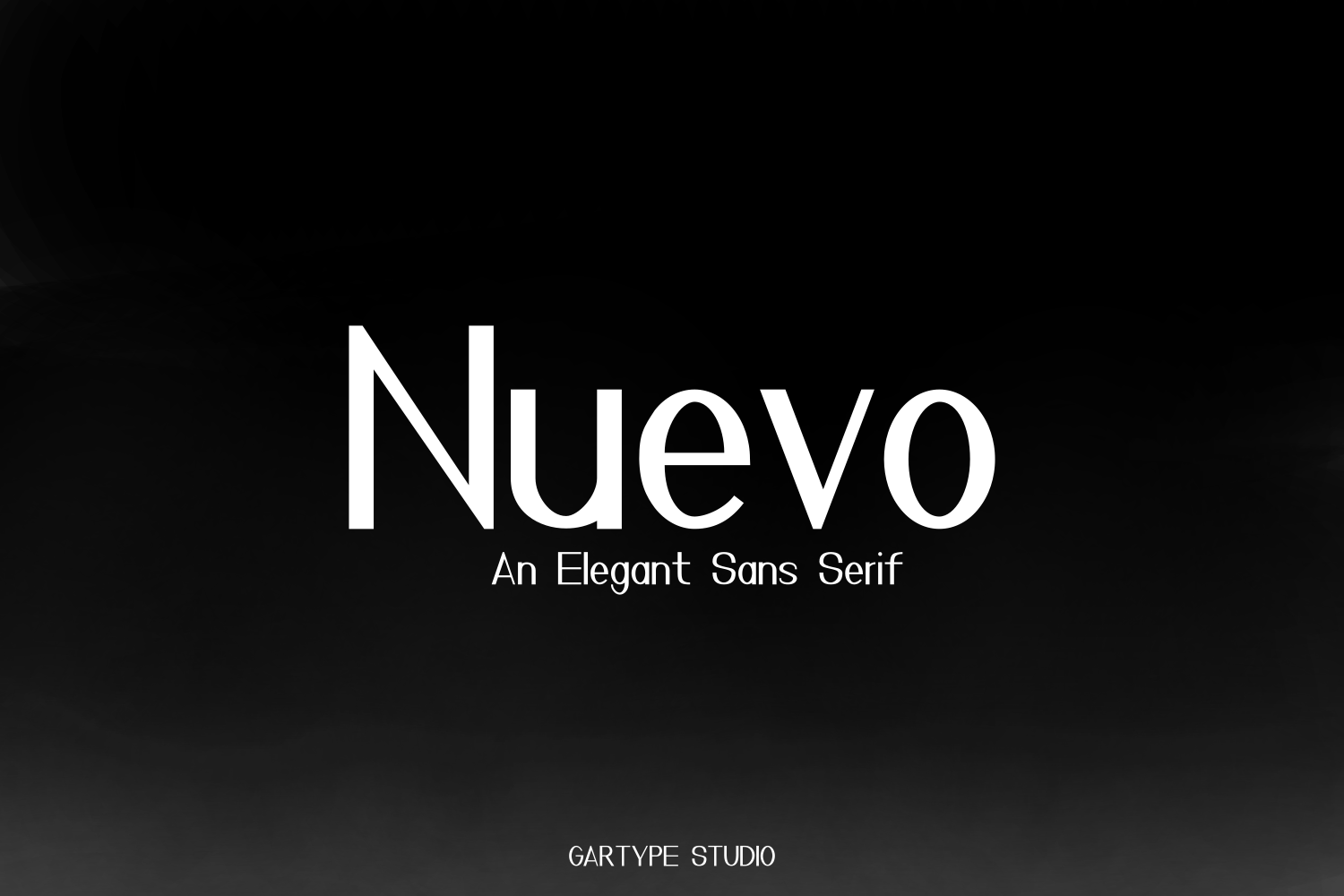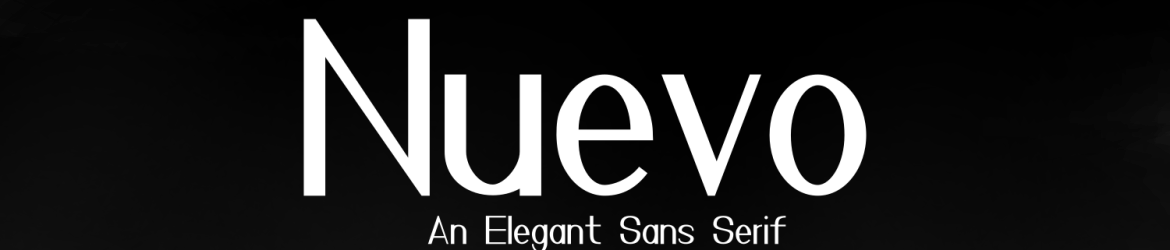
Aqui está uma versão em português do Brasil para a descrição solicitada: Nova Fonte ‘Nuevo Sans’ é uma elegante fóntes sans-serif que traz um toque sofisticado, perfeito para quem busca criar mensagens atraentes e modernas. Ideal para uso em design gráfico variados, como capas de revistas, posters, assinaturas, logotipos, slogans, títulos e muito mais. A ‘Nuevo’ é uma nova opção que combina elegância clássica com um toque atual, perfeita para quem busca uma fóntes moderna que mantenha um padrão de qualidade. Ideal tanto para aqueles que valorizam a estética quanto para os que buscam um visual funcional e clean. Essa fonte é perfeita para criações em diferentes formatos e tamanhos, proporcionando uma experiência criativa variada e versátil. ‘Nuevo Sans’ é uma ótima opção para designers gráficos, oferecendo um estilo moderno que complementa qualquer projeto. Se você busca uma fonte elegante que combine clareza com beleza, a ‘Nuevo Sans’ pode ser o elemento perfeito adicional a seu portfolio de recursos gráficos.